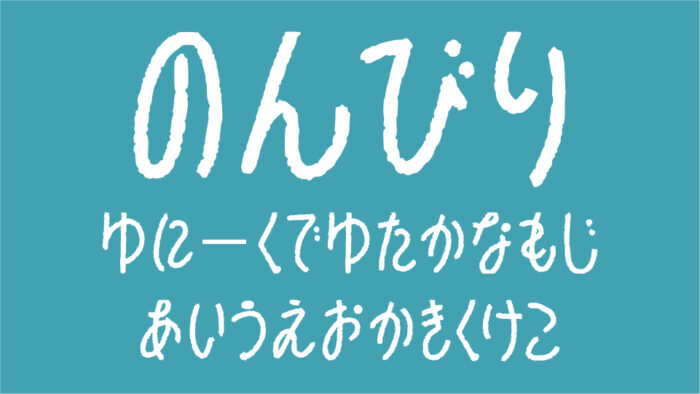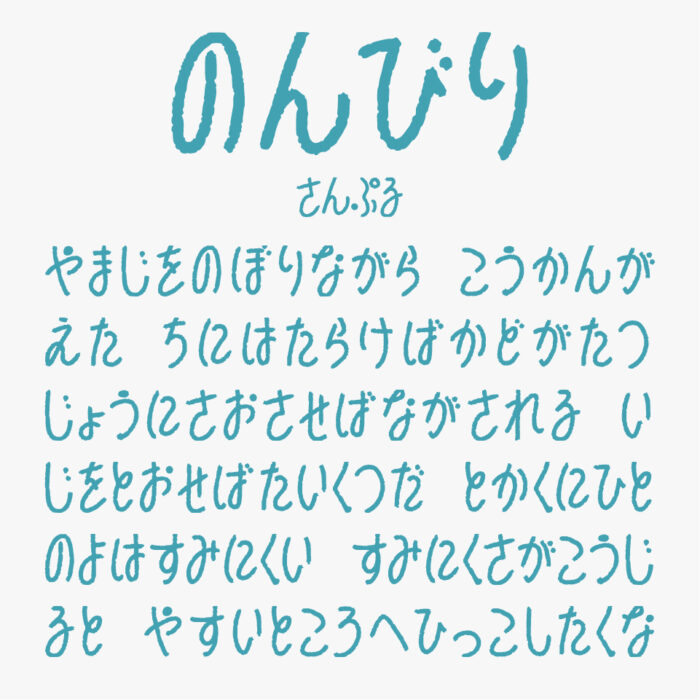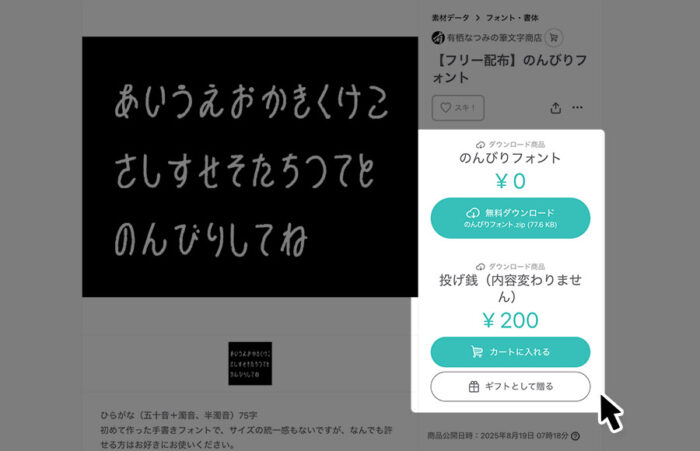
のんびりフォント
のんびりフォントは、ゆったりとした線のリズムと自然体な表情が素敵な手書きのひらがなフォントです。
手書きで書いたような軽やかさがあり、輪郭のギザギザした質感など、肩の力を抜いたのんびりとした空気感がとっても可愛らしいフォントです。気取らない雰囲気を届けたいときにぴったりなフォントです。
収録文字は、ひらがな・カタカナ・漢字、一部の記号が収録されています。
改正版「のんびりフォント_2」もリリースされています。全文字の書き直し&収録数が増えています。